字体设计的概念
文字是一个极其庞大的体系,蕴含着人类集体的智慧,而且对人类社会文明起到了见证作用,西方的文明孕育出拉丁字母,东方的文明诞生了中国汉字。
在字体设计中,首先是将字体定位,对收集到的相关资料进行分析。先考虑要设计的字体所传递的内容。给人留下什么样的印象,然后再用草图记录下来,之后考虑应该使用什么样的颜色、形态和样式,以及要表现的风格。最后提炼综合,设计出良好的字体。
字体设计也是平面设计的主要内容之一,是平面设计的基本构成元素,其功能性已经与平面设计的整体内容相融合。
字体设计在平面设计、标志、包装、广告等传媒设计中具有不可替代的位置,并且在信息传播和产品推广方面发挥了重要作用。
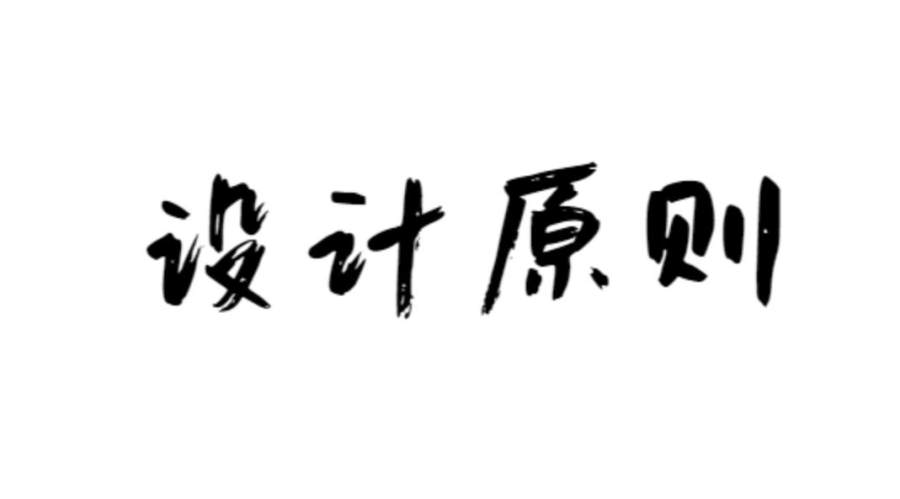
字体设计的意义
字体设计主要的目的就是将文字设计得既美观又实用,而且字体设计广泛应用于版式设计、招贴设计、书籍字体设计和广告设计等领域中,其重点便是文字的笔画、结构和排版等。
文字的功能性在人们的生活中具有广泛的认可度和应用性。一种优秀的字体设计具有独特的艺术气息和美化生活的作用,而且字体的广泛应用也加快了现如今经济时代的信息流通速度,增加了其附加价值。
字体设计的原则
在生活中到处可以看到文字,而且字体设计广泛应用于书籍、报纸、杂志、广告等领域,这些文字都以不同的形式传达着各种各样的信息。因为文字在生活中是十分常见的存在,而且字体经过设计,可以更加形象生动,给人一种美感,因此信息更易传播。
文字只有与众不同,才能更加引人注目。因此,在进行字体设计时,对字体进行统一的形态规范,只有在字体的外部形态上具有鲜明的统一性,才能在视觉上给人以易读性、强调性以及艺术性,从而表达出设计的含义。
易读性原则
在字体设计时,要遵循易读性原则,这是字体设计最基本的准则,在追求字体变化的同时,要使其便于识别。
例如,包装上商品的名称可以进行较大程度的创意设计,因为商品名称文字数量较少,而且较为重要,是商品独特视觉形象的一个组成部分,但商品的成分、规格、功能等大段落的说明文字,则不适宜对文字本身做太多的创意,否则会影响阅读。
强调性原则
在字体设计中,具有强调性的字体设计是指特别着重或着重提出的文字设计。
例如,带有指示类的标识设计,其中的文字可以设计成较为显眼、醒目的特大文字。所以,这就决定了它所涉及的地标、法律、医学、导航等的领域较为严谨。它展现了事件的真实性和严谨性,且优秀的强调性风格的设计可以带动人的思维,具有导航的作用。
艺术性原则
在字体设计中,充满艺术性的字体设计通常灵感都源于生活,是一种简单干净却又不失品位的字体风格。艺术风格的字体设计往往通过图文结合的形式传达所要呈现的内容,既可以打动人的内心、吸引人的注意力,又可以展现出视觉美感。